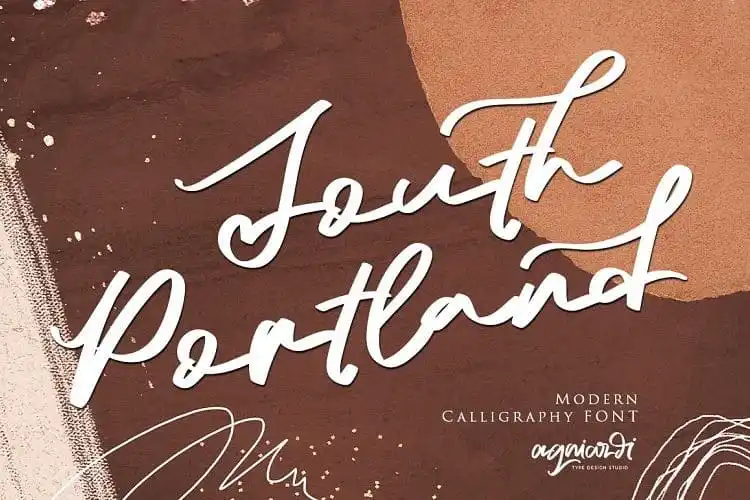
South Portland Script Font – Fonte Grátis
South Portland Script Font
A South Portland Script Font é uma escolha perfeita para qualquer projeto que busca um toque elegante e único. Desenhada pelo designer agniardi, esta fonte contém belas curvas e caracteres alternativos, proporcionando ao seu design um visual singular. Seu estilo se destaca pela forma natural de desenho à mão, combinando características marcantes com uma identidade única. Além disso, a South Portland Script Font oferece opções alternativas meticulosamente criadas para adicionar um toque minimalista e moderno aos seus textos. Esta fonte é ideal para qualquer projeto que deseja dar um toque refinado e distintivo ao texto, seja em logotipos ou materiais publicitários. Sua elegância e personalidade garantem que ela destaque seu design na web ou nos impressos. É uma escolha perfeita tanto para designers quanto para quem quer criar algo de singular e original com sua fonte de escrita à mão.
Designer: agniardi